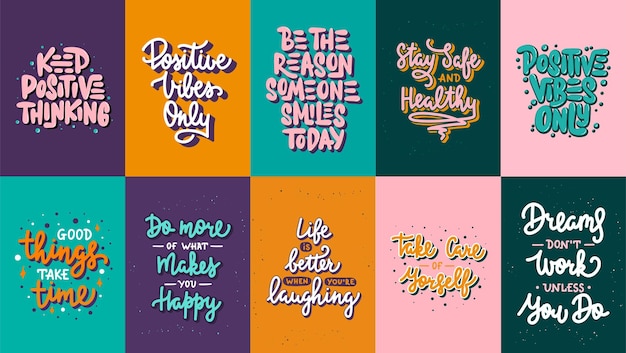
Ensemble de conception de typographie unique dessinée à la main de vecteur de quarantaine pour les impressions de décoration d'affiches
Ensemble de conception de typographie unique dessinée à la main de vecteur de quarantaine pour les affiches Lettrage manuscrit